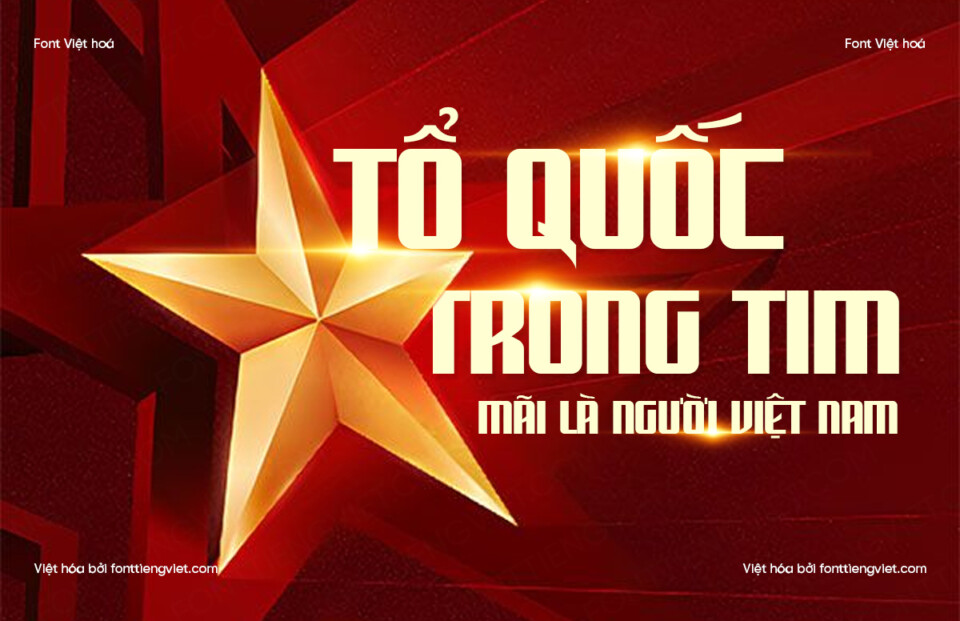
Font Việt hóa 1FTV VIP Freshome – Font đại lễ quốc khánh
Font Việt hóa 1FTV VIP Freshome – Font đại lễ quốc khánh: Sự lựa chọn hoàn hảo cho thiết kế chào mừng ngày Quốc khánh 2/9
Giới thiệu về Font Việt hóa 1FTV VIP Freshome – Font đại lễ quốc khánh
Trong không khí hân hoan chào mừng các ngày lễ lớn của dân tộc, việc lựa chọn một bộ Font Miễn Phí phù hợp để truyền tải thông điệp yêu nước là điều vô cùng quan trọng. Font Việt hóa 1FTV VIP Freshome – Font đại lễ quốc khánh được ra đời với mục đích tôn vinh vẻ đẹp hiện đại nhưng không kém phần trang trọng, phù hợp cho các thiết kế banner, poster và ấn phẩm truyền thông kỷ niệm ngày Quốc khánh Việt Nam. Với các đường nét thanh thoát, mạnh mẽ và bộ dấu tiếng Việt được tối ưu hóa hoàn toàn, bộ font này giúp các bạn học sinh và thầy cô giáo dễ dàng tạo ra những tác phẩm đồ họa ý nghĩa ngay trên máy tính của mình mà không gặp bất kỳ lỗi hiển thị nào.
Đặc điểm nổi bật của Font Việt hóa 1FTV VIP Freshome – Font đại lễ quốc khánh
Thiết kế hiện đại và tinh tế
Bộ Font Việt hóa 1FTV VIP Freshome – Font đại lễ quốc khánh sở hữu phong cách sans-serif hiện đại, mang lại cảm giác sạch sẽ và chuyên nghiệp. Các chữ cái được thiết kế với độ dày vừa phải, giúp tăng khả năng đọc trên cả định dạng in ấn lẫn kỹ thuật số. Điều này đặc biệt hữu ích khi các bạn thiết kế các slide bài giảng hoặc bảng tin nhà trường để chào mừng đại lễ, nơi sự rõ ràng của thông tin luôn được ưu tiên hàng đầu.
Hỗ trợ tiếng Việt trọn bộ và tính linh hoạt cao
Điểm mạnh nhất của Font Việt hóa 1FTV VIP Freshome – Font đại lễ quốc khánh chính là khả năng hiển thị tiếng Việt xuất sắc. Các dấu thanh như dấu huyền, sắc, hỏi, ngã, nặng được đặt ở vị trí cân đối, không bị chồng chéo hay quá cao, tạo nên sự hài hòa tuyệt đối cho câu văn. Ngoài ra, font chữ này còn rất linh hoạt, bạn có thể sử dụng nó cho các tiêu đề chính nổi bật hoặc các đoạn văn bản ngắn mô tả về lịch sử hào hùng của dân tộc trong dịp lễ 2/9 sắp tới.
Ứng dụng Font Việt hóa 1FTV VIP Freshome trong thiết kế học đường
Thiết kế băng rôn và khẩu hiệu chào mừng
Sử dụng Font Việt hóa 1FTV VIP Freshome – Font đại lễ quốc khánh để làm tiêu đề cho các tấm băng rôn treo tại cổng trường hay trong lớp học sẽ tạo nên điểm nhấn ấn tượng. Sự kết hợp giữa màu đỏ rực rỡ của lá cờ Tổ quốc và phông chữ trắng hiện đại sẽ giúp thông điệp “Chào mừng ngày Quốc khánh 2/9” trở nên trang trọng và truyền cảm hứng hơn bao giờ hết cho toàn thể giáo viên và học sinh.
Làm slide thuyết trình về lịch sử dân tộc
Trong các tiết học về lịch sử hoặc hoạt động ngoại khóa, việc sử dụng Font Việt hóa 1FTV VIP Freshome – Font đại lễ quốc khánh trong bài thuyết trình giúp nội dung trở nên lôi cuốn. Các em học sinh có thể dễ dàng trình bày các mốc son chói lọi của đất nước một cách chuyên nghiệp, giúp người xem dễ dàng ghi nhớ kiến thức thông qua những dòng chữ đẹp mắt và dễ đọc.
Kết luận về bộ phông chữ đại lễ
Việc sở hữu một bộ font chữ chất lượng không chỉ giúp công việc thiết kế trở nên thuận lợi mà còn góp phần thể hiện sự trân trọng đối với những giá trị văn hóa. Hãy tải ngay Font Miễn Phí, Font Việt Hóa, Font Việt hóa 1FTV VIP Freshome – Font đại lễ quốc khánh để bắt đầu sáng tạo những ấn phẩm tuyệt đẹp cho mùa lễ hội năm nay. Đây chắc chắn là công cụ không thể thiếu trong thư viện đồ họa của mọi nhà thiết kế yêu thích phong cách Việt.